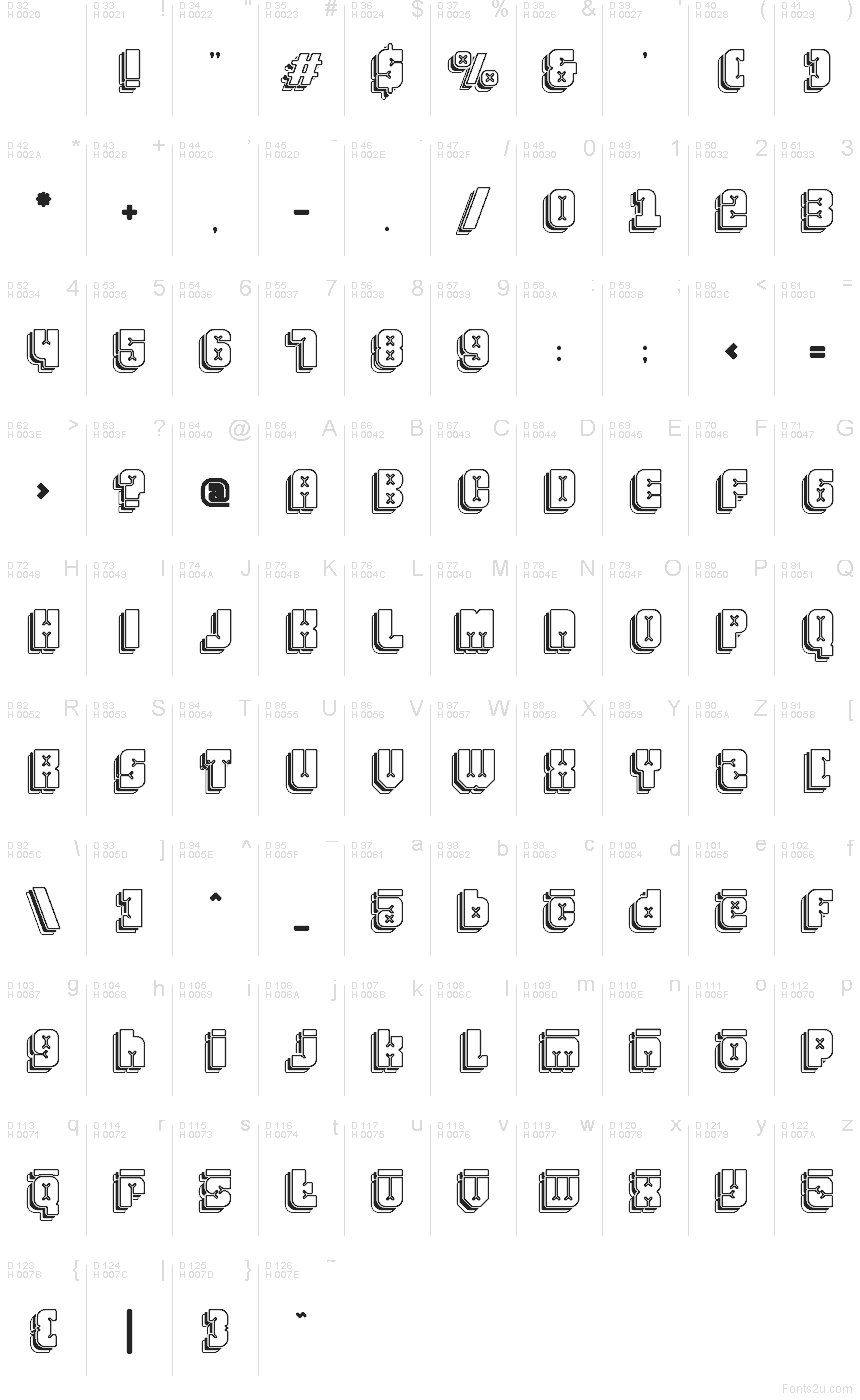
Friez Ten od Putracetol Studio je groovy 3D font typu display, tvořený zaoblenými obdélníkovými tvary a vrstvenými stíny, které písmu dodávají měkkou, plastickou hloubku. Díky opakujícím se zaobleným rohům a zářezům působí design graficky uceleně, připomínaje spíše tvarované nápisy než běžnou retro variaci.
Široká silueta dodává krátkým titulkům na síle v plakátech, cover artech, logotypech, obalech a grafice pro sociální sítě, kde stínovaná konstrukce může být ústředním prvkem kompozice. Friez Ten se skvěle hodí i na nálepky a nadpisy akcí, zejména pokud hledáte výrazné konturované tvary, které fungují stejně dobře jako dekorativní objekty i jako písmo.
Friez Ten